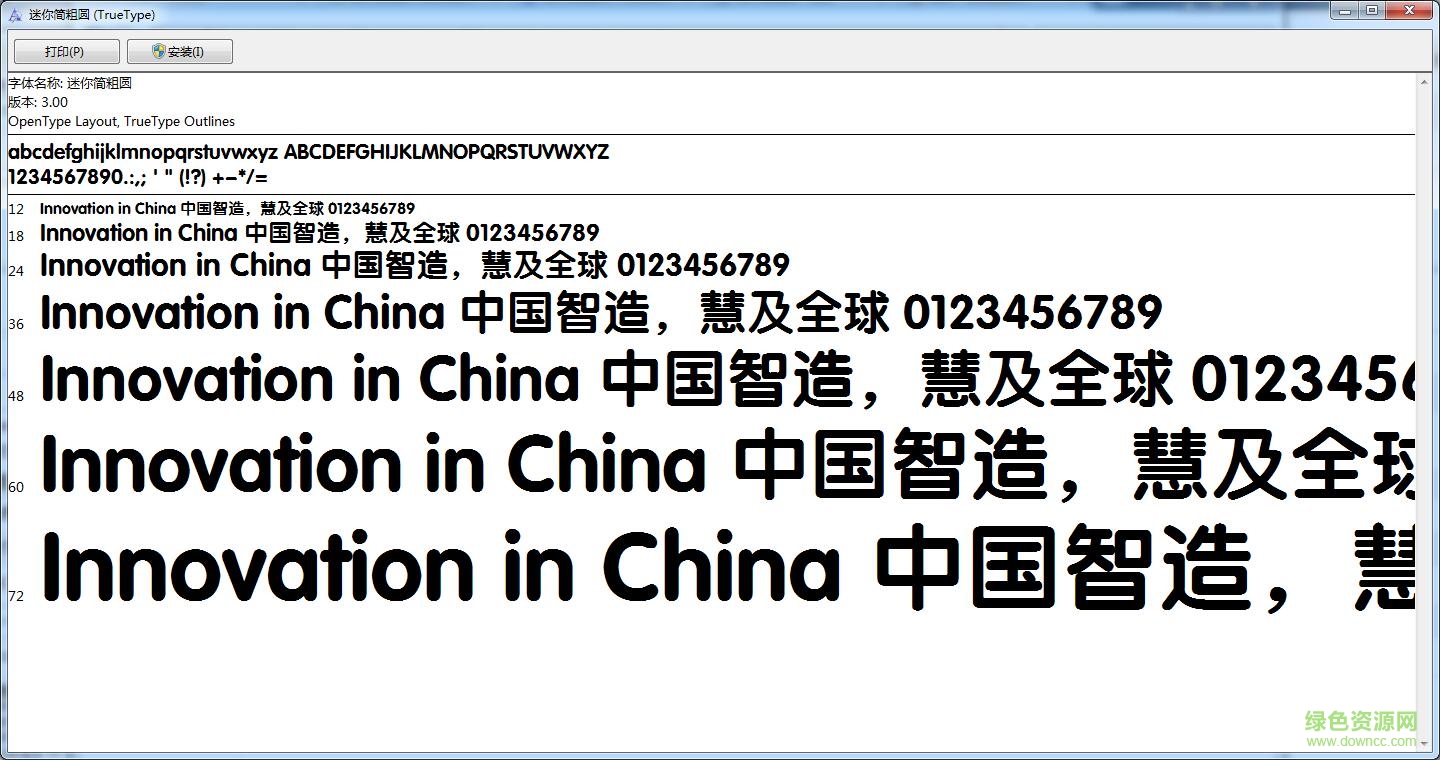
迷你簡(jiǎn)粗圓字體是一款免費(fèi)的中文字體。這個(gè)字體屬于那種圓形的字體,做名片、公司設(shè)計(jì)logo的時(shí)候常常使用!非常的美觀醒目,喜歡的用戶(hù)可以免費(fèi)下載!
迷你簡(jiǎn)粗圓是在粗圓字體的基礎(chǔ)上開(kāi)發(fā)的一款簡(jiǎn)體中文漢字,該字體粗細(xì)適中,大方得體,整體效果十分出色,并且字庫(kù)完整,可以適用于名片設(shè)計(jì)、平面設(shè)計(jì)、廣告設(shè)計(jì)、報(bào)紙雜志、企業(yè)LOGO、商標(biāo)注冊(cè)、電視臺(tái)廣告等領(lǐng)域!需要的用戶(hù)歡迎來(lái)綠色資源網(wǎng)下載使用。
1.粗細(xì)適中,大方得體
2.可以適用于名片設(shè)計(jì)、平面設(shè)計(jì)等行業(yè)領(lǐng)域